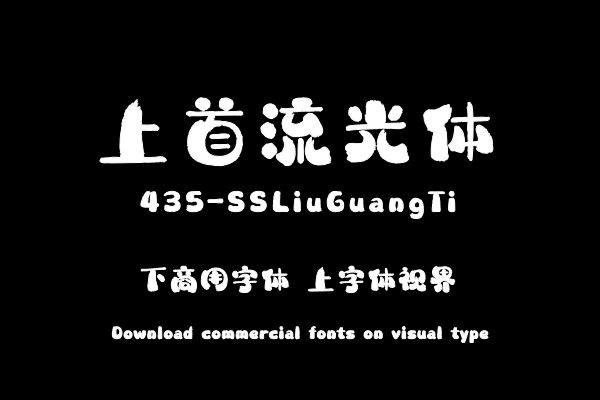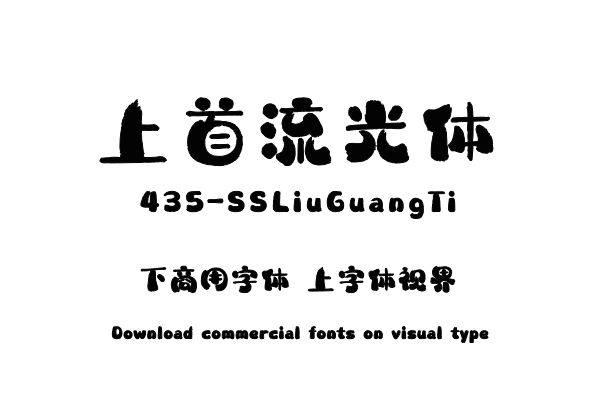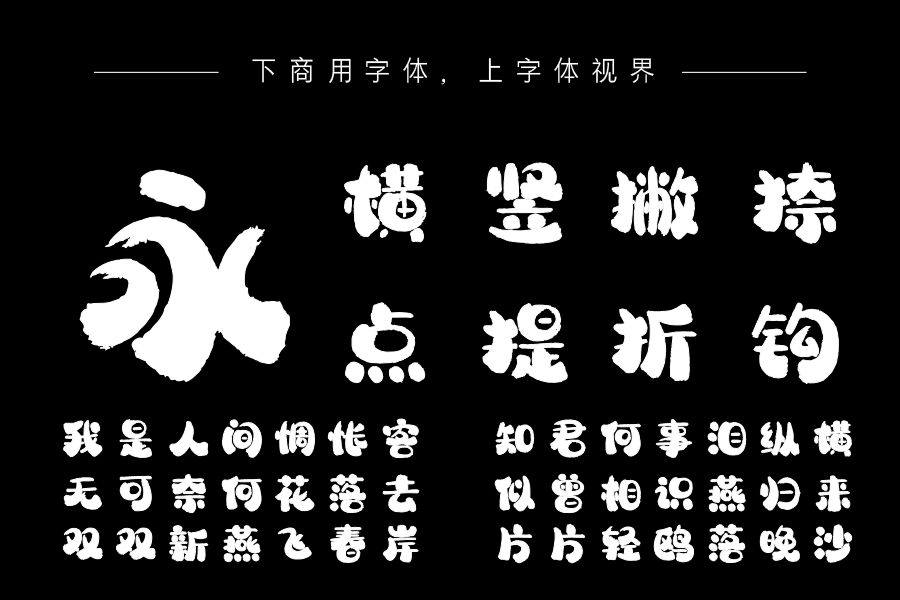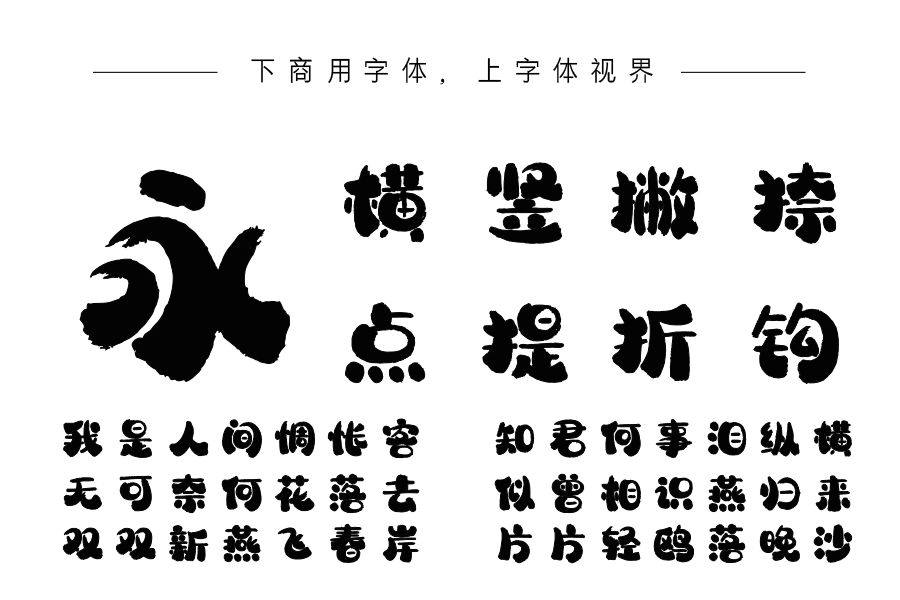
上首流光体,简体中文约6763字。这套字体在字形设计上,融合古朴与灵动,笔画如流转光影,既有圆润舒展的形态,又暗含遒劲张力,似时光在笔墨间缓缓淌过。在笔画细节处......购买须知:“下载服务费”与“字体VIP”所获得字体 仅用于个人非商用, 商用请联系付费授权。本字体为电脑用字,手机没有root权限不支持直接手机换字(手机如何root,请自行百度搜索教程)。购买前请先 了解清楚后再付款 ,字体为虚拟产品无法回收 一旦购买不支持退款。